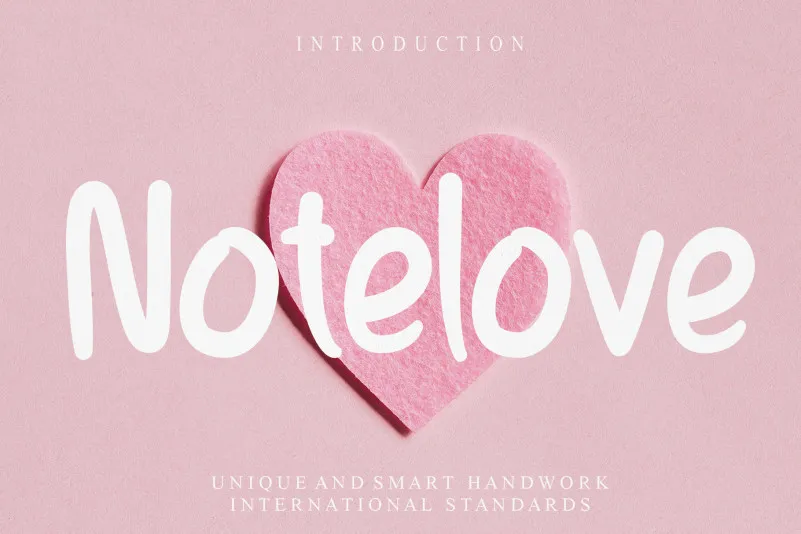
Sinta-se bem-vindo ao universo encantador e vibrante do ‘Notelove Display Font’. Esta fonte é uma jóia para qualquer designer que busca tornar seus projetos ainda mais divertidos, especialmente no estilo Playful. Desenvolvida pelo talentoso designer creativeletter, essa peça de arte digital traz um toque de frescor e vivacidade à sua composição. Com linhas suaves e formas arredondadas, a ‘Notelove Display Font’ é perfeita para personalizar títulos, slogans ou qualquer elemento visual que deseje destacar em seu design. Seja ele uma campanha publicitária, um flyer de eventos ou até mesmo um calendário, essa fonte trará vida e encanto à sua mensagem. Através de suas linhas criativas e texturas divertidas, a ‘Notelove Display Font’ vai deixar seu público perceber que você está sempre ligado às últimas tendências e práticas da design gráfico. Sua experiência única no estilo Playful irá garantir que seus designs serão lembrados por toda sua elegância e encanto. Estamos ansiosos para vê-lo explorar as possibilidades criativas do ‘Notelove Display Font’. Experimente-o em seu próximo projeto e descubra o quanto a diversão pode fazer pela qualidade de um bom design.